大写字母
制作大写字母应该按照与制作小写字母非常类似的模式。你以一些关键字符为开始,这些关键字符的形状和特性影响到那些使用公用形状的字符。就像设计小写字母时那样,字母使用的频率也是字母的选择的一个重要因素。
首选要设计的两个字母是“H”和“O”。这些字母设计时不应该只注意他们之间的互相关系,也要同时注意与已有的小写字母的关系。
在这个阶段你应该确定小写字母和大写字母的比例。你可能希望调整你的小写字母的顶部或者底部,或者调整大写字母使得与小写字母的比例适合你设计的目的。
大写字母的描绘宽度经常需要比小写字母重一点。你可能希望建立插入试验来快速找到应该重多少。
下一个考虑添加的字符集时 A E S I N 和 P 与 D 中的一个,可能还有 V。
根据你已经制作的字体的样式,你可能发现大写字母需要比小写字母更多的宽度上的变化。E、S 和 P 的宽度大体上可能比H更窄或者近似。
通常说来,N 和 V 经常类似于 H 但是更宽一点。
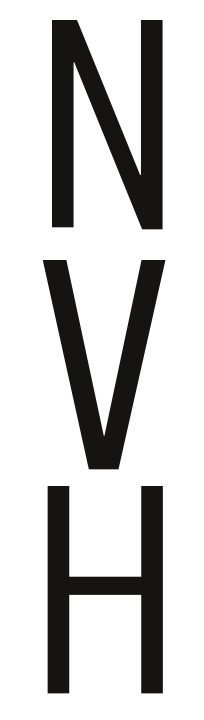
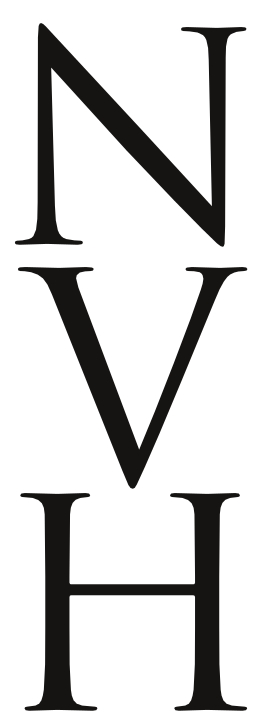
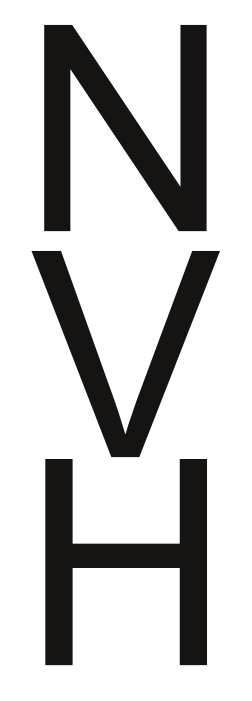
D 可能类似于 H 或者更宽一点点。
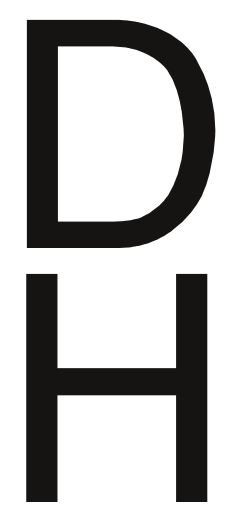
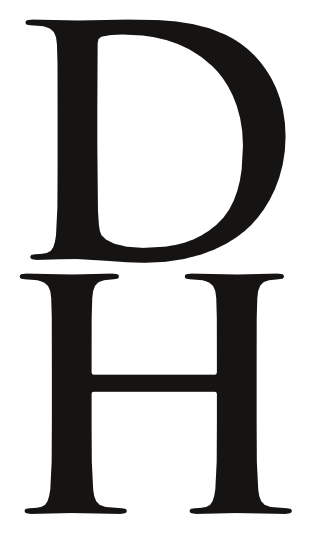
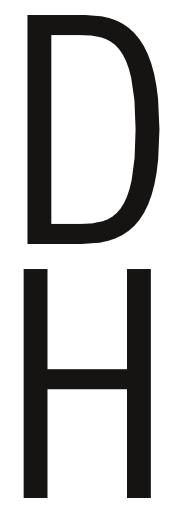
O 的形状可以在设计 C、G 和 Q 时参考很多。H 的形状会让你知道 I 和 J 和 B D E F K L P R 的左边的一些信息。
它也告诉你 T 和 U 的一点信息。A 的形状可以让你知道非常多 V 的信息。
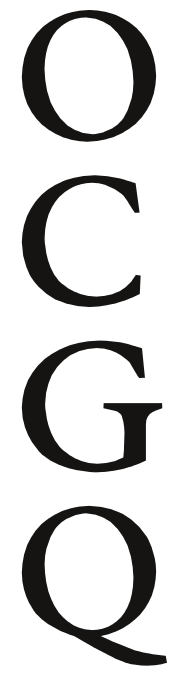
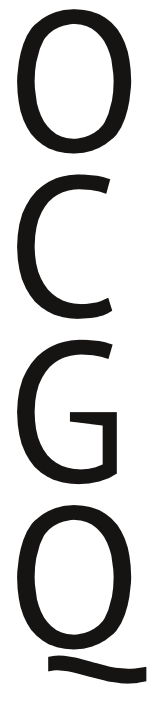
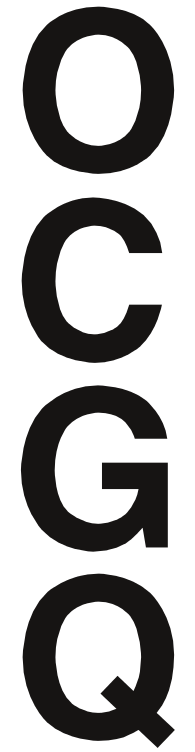
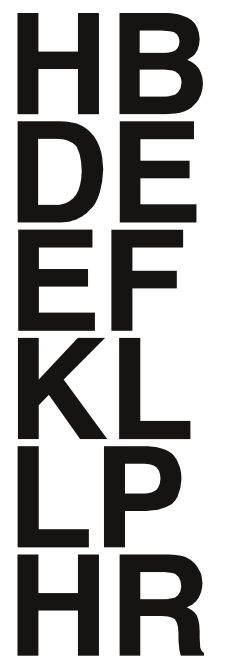
V 的形状和比例告诉你一点如何设计 Y W X 的信息。Z 的形状是与众不同的。